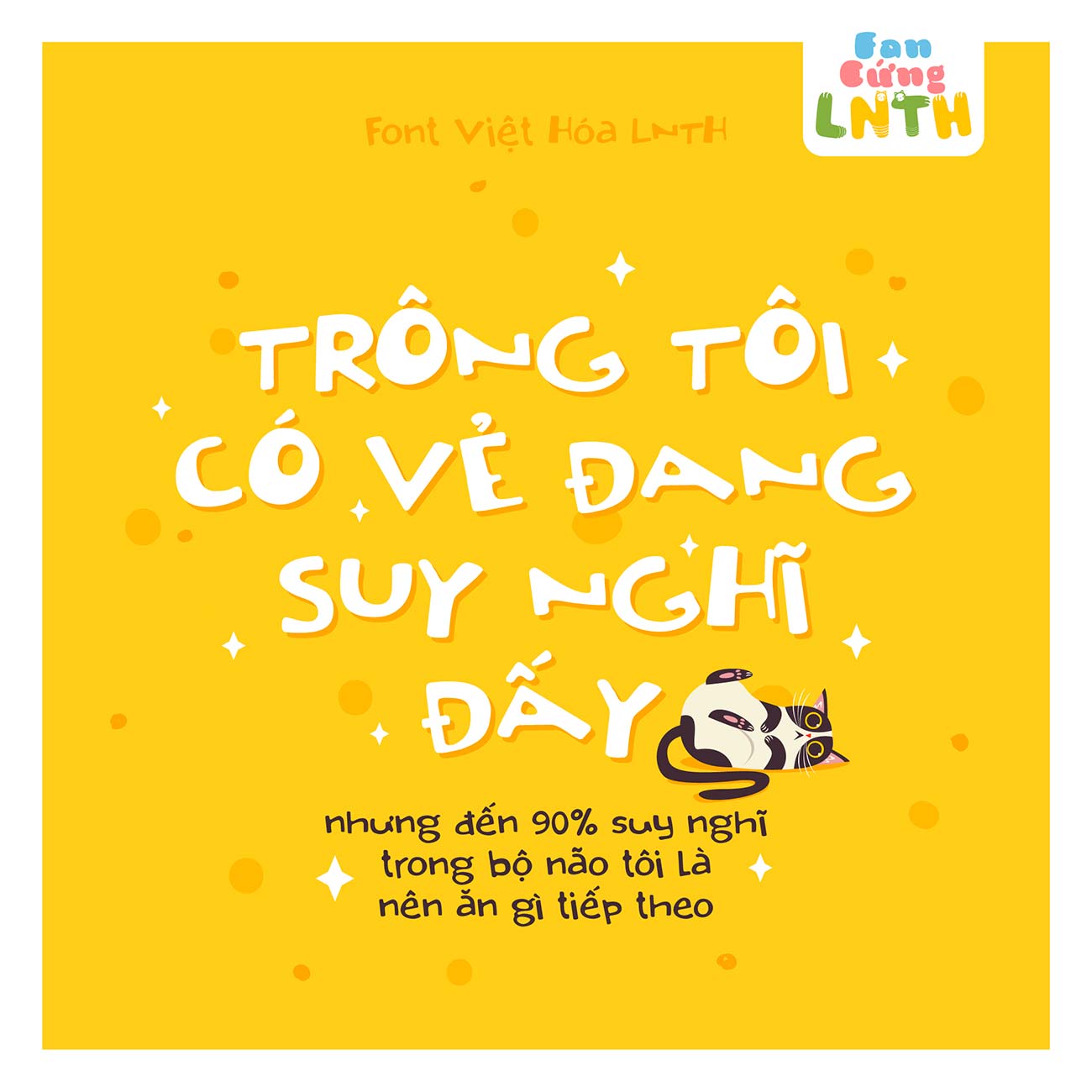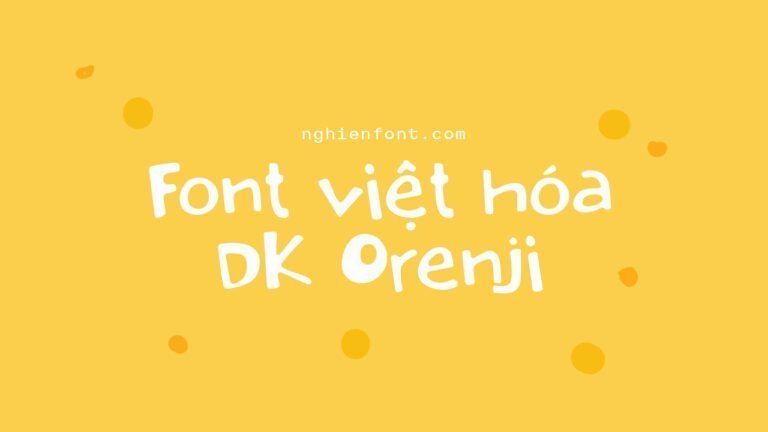
LNTH DK Orenji là một kiểu font vui nhộn với các nét chữ được thiết kế kiểu nguệch ngoạc rất đẹp mắt và dễ thương. Font chữ phù hợp cho các thiết kế kiểu vui vẻ.
DK Orenji còn có một số hình tượng có hình dạng độc đáo, đi kèm với hình mặt cười khúc khích, cái ôm và nhiều dấu phụ hơn để bạn tha hồ sáng tạo cho các thiết kế của mình.